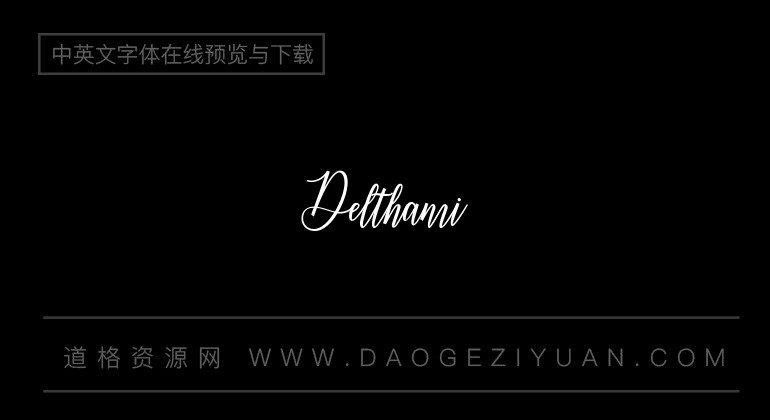
Delthami
Delthami 字体是一款受到西班牙文化和传统影响的现代字体。它具有简洁、优雅和细腻的外观,适合用于报纸、杂志、书籍、广告等多种场合。它的字形和线条比较细,让人感觉更加清新和精致,可以用来创造出独特的设计风格。它的字母间距也较大,使文字更易于阅读。
Delthami是一款非常不错的手写艺术字体,具有很好的视觉感,适合于文化类的宣传设计、商业类品牌的广告和产品包装设计以及个性化文字排版等较多场景。